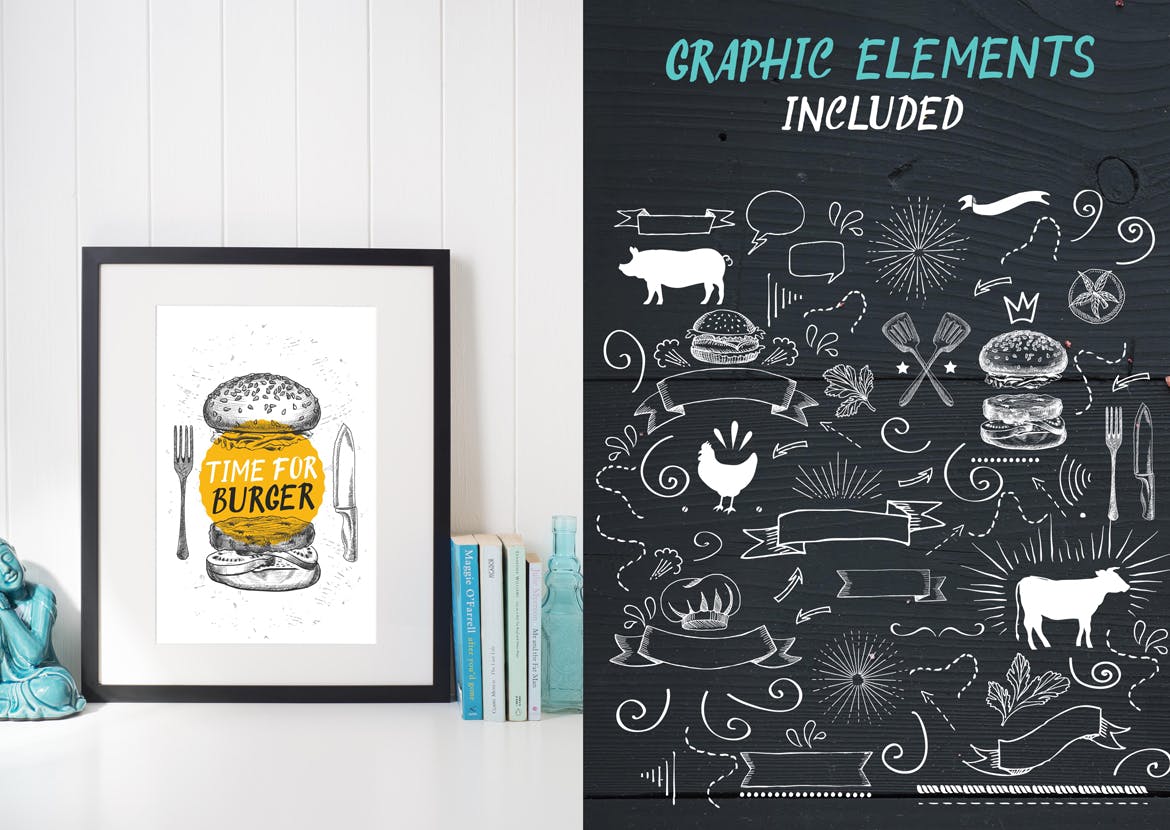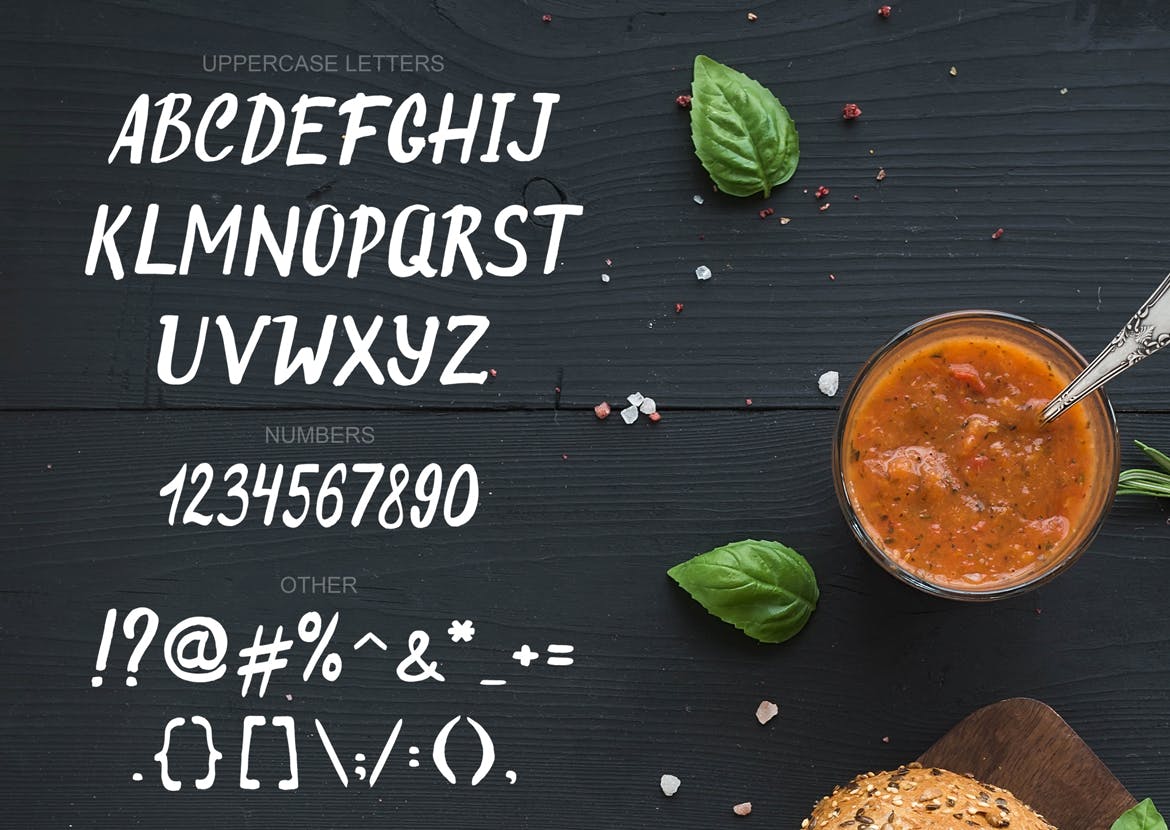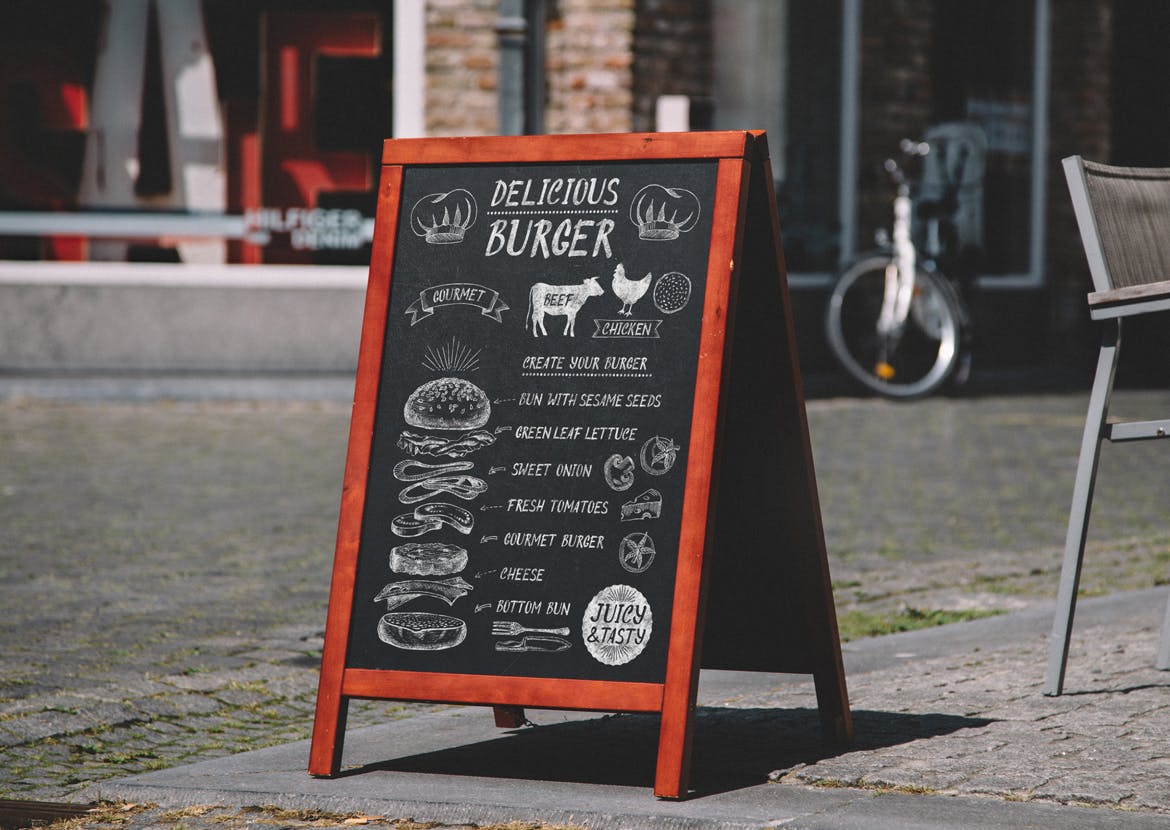
Original Burger Font
فونت Original Burger
فونت Original Burger یک فونت دست‌ساز است که شامل حروف بزرگ، علامت‌های نگارشی و اعداد می‌باشد. این فونت شامل الفبای بنیادی لاتین از A تا Z است و همچنین عناصر گرافیکی دودیلی را به همراه دارد.